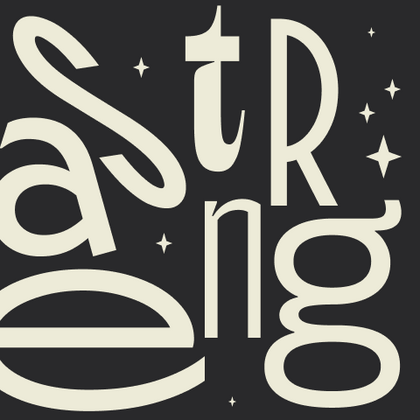
TT Polihaus — экспериментальный гротеск, который на первый взгляд кажется обычным, а затем разбирается на части, превращаясь в трафаретный узор.
Странные шрифты Weird
Текст со смелыми экспериментами в типографике ломает привычные представления о форме букв и символов. Дизайн странных шрифтов балансирует на грани искусства и функциональности: от психоделических завитков до гротескных деформаций. TypeType предлагает необычные гарнитуры, где каждый элемент бросает вызов традициям, оставаясь при этом рабочим инструментом дизайнера. Такие шрифты не только передают текст, но и создают мощный визуальный акцент, превращая любое сообщение в арт-объект.
TT Nooks Script — шрифт с уникальным рисунком, который не имеет прямых аналогов.
TT Dott — экспериментальный пиксельный гротеск, в котором за основу пикселя взят круг. Это пластичный и необычный акцидентный шрифт, вызывающий ассоциации одновременно с вышивкой и техно-вечеринками.
В TT Frantz можно найти небольшие отсылки в эстетике арт-деко, которые выражены в сильно заниженной или наоборот сильно завышенной талии у букв. Кроме того, в зависимости от положения ползунка регулировки оси, у некоторых букв изменяется закрытость апертуры.
TT Quaris — изысканная и современная ленточная антиква. Перед разработкой этой гарнитуры мы провели глубокое исследование архетипов ленточных антикв.
TT Modernoir — акцидентный гротеск с разноширинными пропорциями. Плавные линии и изящные формы ар-нуво в этом шрифте сочетаются с ритмичностью и импровизационной свободой джаза.
TT Fellows — гуманистический гротеск с механистическими мотивами. Открытые формы, дружелюбно-нейтральный характер тонких весов и ещё более мягкий характер в жирных начертаниях.
TT Gertika — геометрический гротеск с динамичным характером и танцующим ритмом. Идея шрифта зародилась из леттеринга на американском плакате второй половины 30-х годов.
TT Biersal — акцидентный гротеск со свободным, озорным и авантюрным характером. Отправной точкой для его создания послужил немецкий плакат начала 30-х годов. Мы хотели сохранить не только пропорции, но и ощущение небрежности, живости леттеринга из референса.
TT Paplane — акцидентный сквадраченный гротеск. Так, характерные черты этого гротеска — сквадраченные формы, 45-градусные срезы и обтекаемые внешние контуры.
TT Carvist — современный экспериментальный гротеск со сверхузкими пропорциями. Название гарнитуры отсылает к резьбе по камню: характерные черты этого шрифта — геометричность и брутальность.
TT Espina — дисплейная антиква с выразительными засечками. При ее создании дизайнеры вдохновлялись исторической формой буквы «O», которая приобретала ромбовидную форму из-за качества печати. В каждую букву хочется всматриваться, так что заголовки, оформленные TT Espina, точно привлекут внимание.
TT Norms® Pro — один из самых востребованных шрифтов студии, выбор известных мировых брендов. Более трёх переизданий за семь лет, первые строчки на MyFonts, десятки кастомизаций. Это «рабочая лошадка», которая станет незаменимой базой любой шрифтовой коллекции.
TT Commons™ Pro — один из самых востребованных шрифтов студии. Сфера его применения практически безгранична! Беспроигрышный вариант для тех, кто ищет стильный и функциональный базовый шрифт для любых проектов.
TT Hoves Pro — скандинавский гротеск с нейтральным, но в то же время узнаваемым характером. Это удобный и функциональный, при этом стильный и эстетичный инструмент для дизайнеров. Такой шрифт позволит вам решать множество разноплановых задач!
TT Supermolot Neue — непобедимое оружие в борьбе за стиль! Это технологичный модульный гротеск с футуристическим настроением и мощным функционалом. Шрифт идеально подойдёт для оформления компьютерных игр и множества других проектов.
TT Firs Neue — сбалансированный гротеск со скандинавскими мотивами. Это выразительный и привлекательный, при этом лаконичный и универсальный в использовании шрифт. Переиздан дважды, чтобы быть безупречным.
TT Rounds Neue — мягкий и дружелюбный шрифт, который умеет быть разным. В тонких начертаниях он выглядит минималистично и нейтрально. В жирных же — «надувается» и округляется, приобретая инфантильные черты.
Любите ли вы раннюю советскую визуальную культуру как любим её мы? Несмотря на свое советское прошлое, TT Bricks выглядит очень свежим и визуально мощным шрифтовым семейством, которое отлично вписывается в современное медиапространство.
TT Slabs является простой и геометричной брусковой гарнитурой и отлично подойдет вам, если для ваших проектов вы ищете универсальный шрифт с широкими пропорциями.